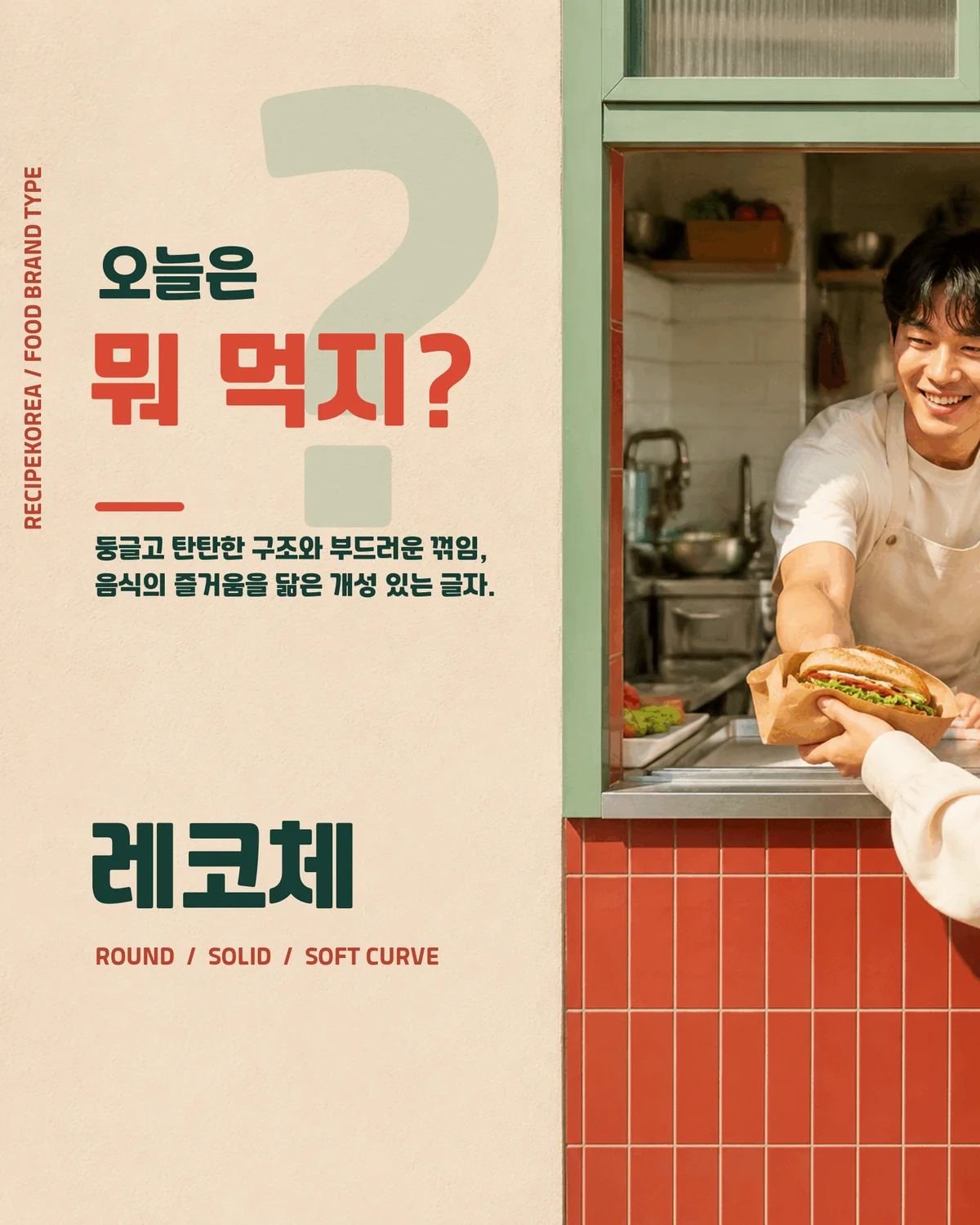
레코체 — 레시피코리아에서 배포하는 무료 폰트입니다. 둥글고 탄탄한 글자 구조에 부드러운 꺾임을 더한 개성 있는 고딕체
레시피코리아가 2020년에 배포한 서체입니다. 레시피코리아는 외식과 식당 창업 정보를 다루는 커뮤니티이고, 이름의 레코는 그 줄임말로 보입니다.
만든 이유가 이 서체의 전부입니다. **소상공인들이 저작권 문제없이 쓸 수 있게끔** 개발했다는 것입니다. 식당이나 카페를 하는 분들이 메뉴판과 간판, 전단지를 만들 때 폰트 걱정을 하지 않도록 만든 폰트입니다.
먼저 분류를 바로잡을 것이 있습니다. 이 서체는 **손글씨가 아니라 두꺼운 둥근 고딕**입니다. 배포처가 쓴 조형 설명은 없어 형태는 파일을 보고 적습니다. 받침 유무에 따른 높이 차가 거의 없는 네모틀이고 낱자는 정사각형에 가까우며, 자면을 넉넉히 채워 굵고 진합니다. 멀리서 읽는 간판이나 썸네일에 힘이 실립니다.